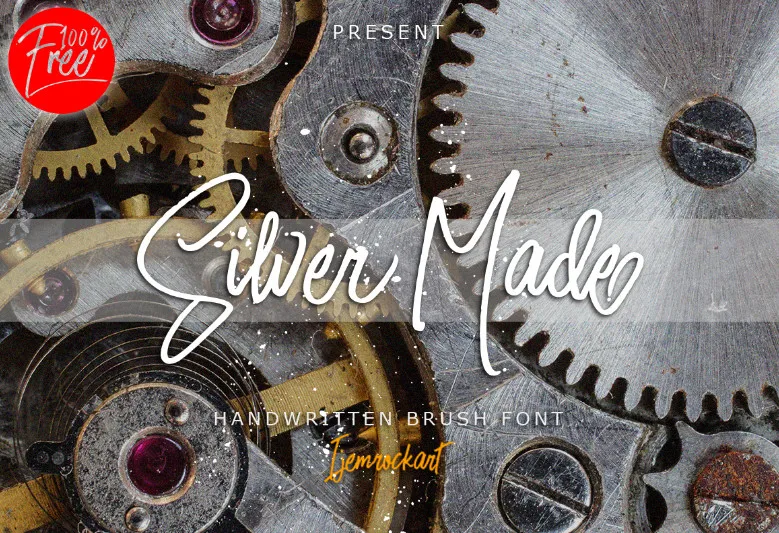
Silver Made Script Font – Download Grátis
A fonte ‘Silver Made Script Font’ do tipo Brush Fonts apresenta a beleza única dos traços de pena manual, criando uma atmosfera elegante e inovadora para projetos de letraing e marcação. Esta fonte foi projetada por Ijemrockart e compartilhada pelo Pathero Studio e é um modelo gratuito que inclui duas versões alternativas. Perfeita para aqueles que desejam adicionar um toque elegante e único a seus projetos de letraing, ou seja, desde a criação de cartazes de casamento até lindas molduras para sua casa. Ou simplesmente use-a em pequenas empresas, capas de livros, papelaria, marketing, revistas e muito mais. O Pathero Studio oferece apoio para ajudá-lo a explorar as infinitas possibilidades desta fonte única e sofisticada.